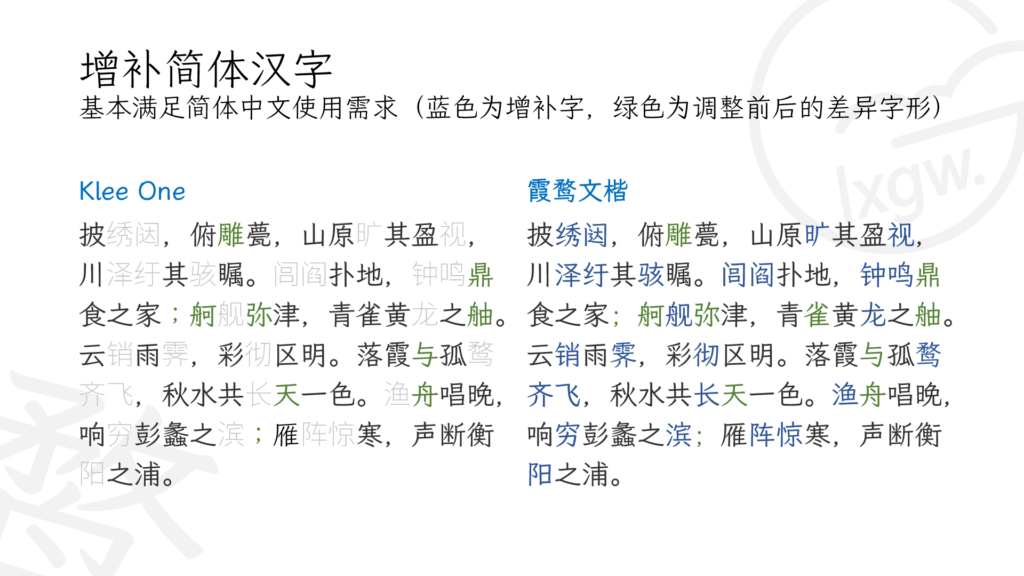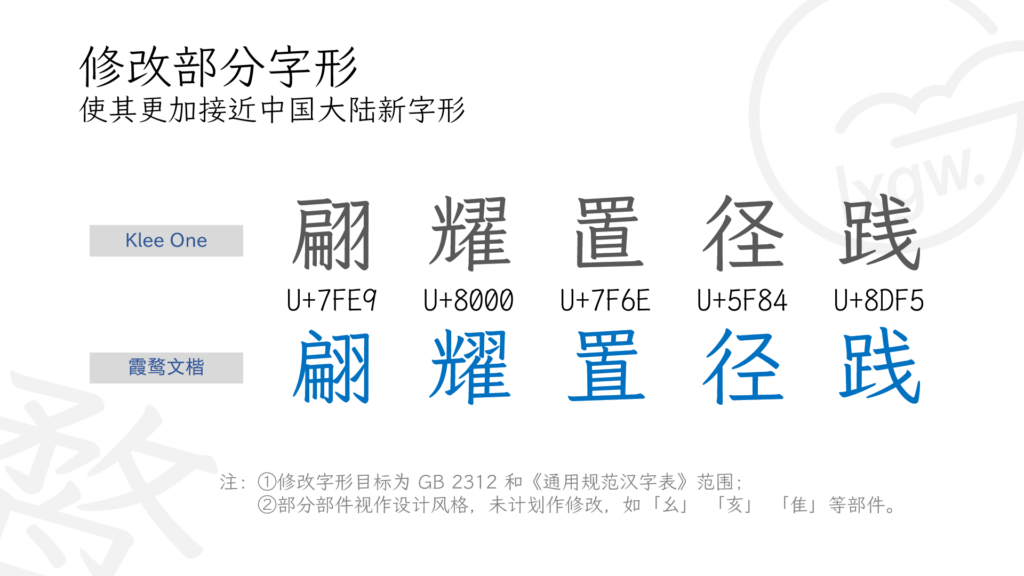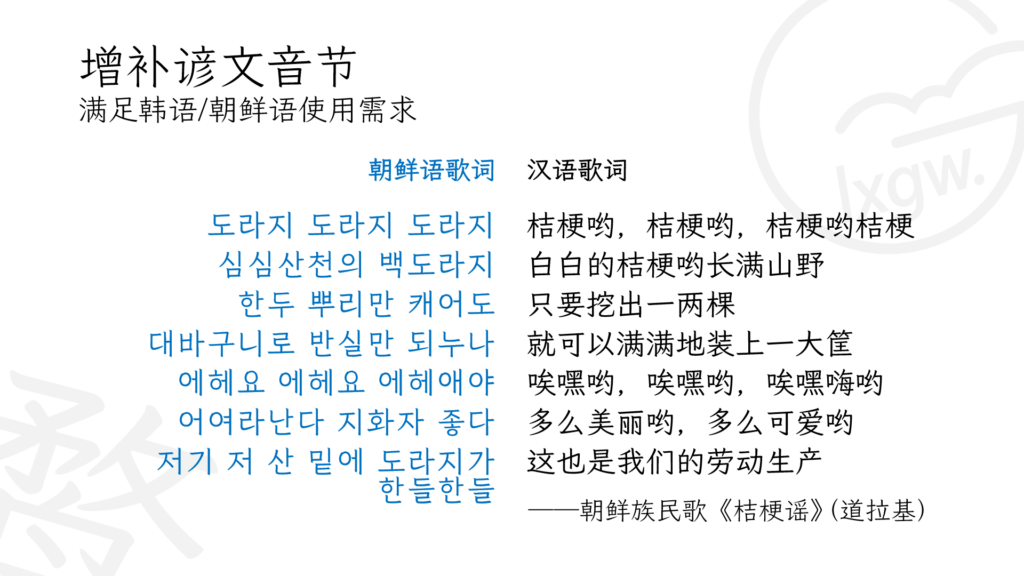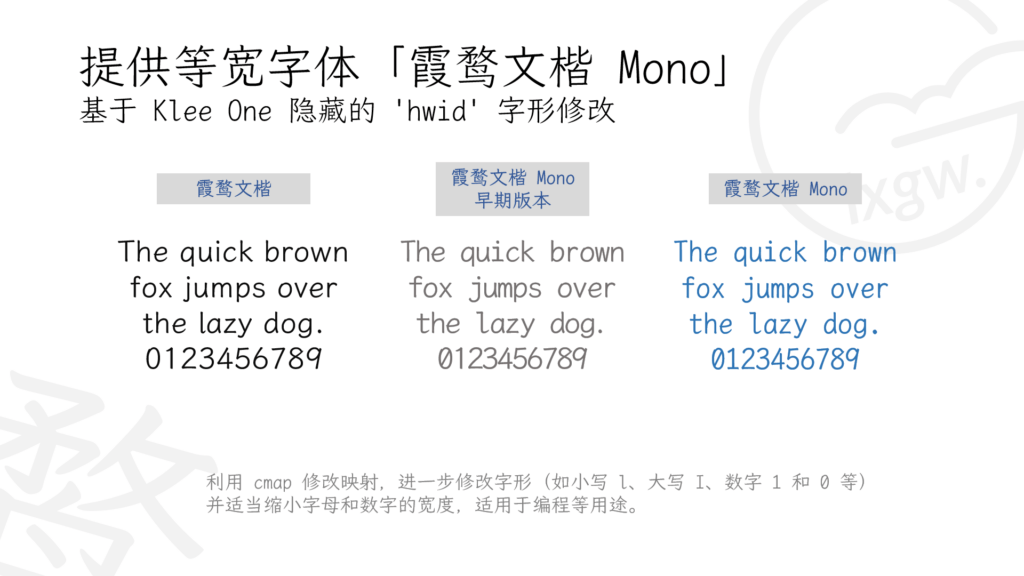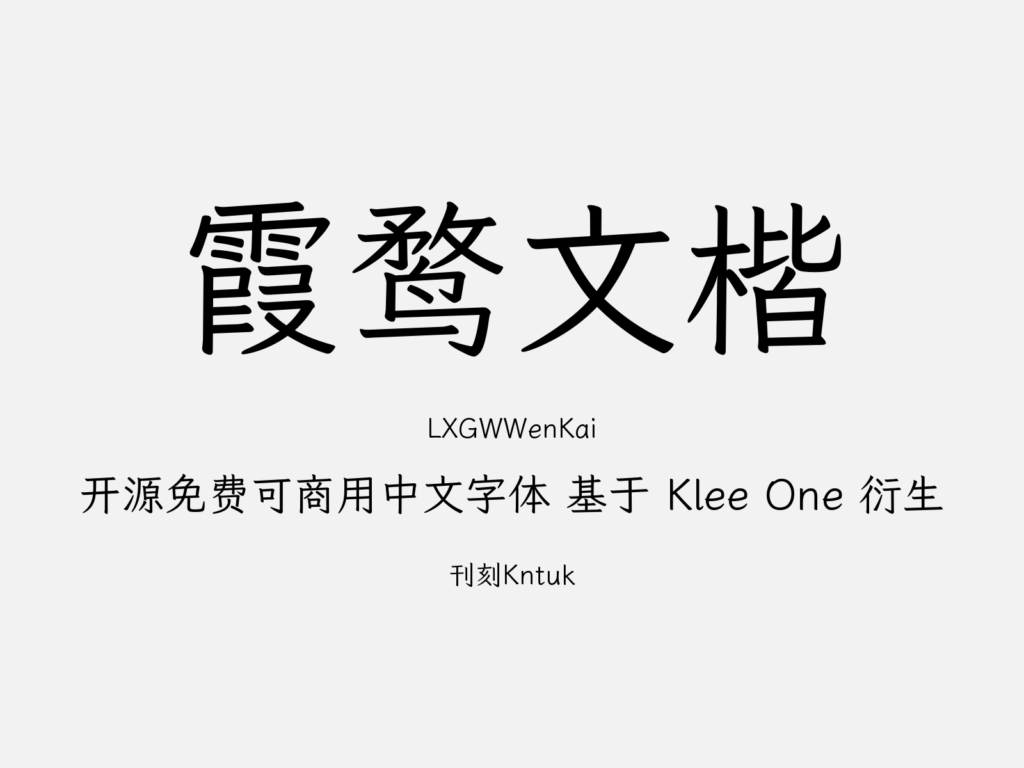
2020年12月,日本知名字体厂商FONTWORKS在GitHub上开源发布了七款日文字体,包括Train、Klee、Stick、Rock-n-Roll、Reggae、Rampart和DotGothic16,均基于SIL Open Font License 1.1授权。这七款字体各有特色,其中字符数量最多的是Klee。它带有日本教科书体风格,融合了仿宋和楷体的特点。一些字体DIY爱好者曾用仿宋等字体补全Klee,移植为iOS、Android等手机系统的美化字体,受到不少玩机发烧友欢迎。不过这种补全方式存在不足:一方面,原字体与补字体存在差异,导致不同文字混排时产生违和感,比如Klee原有汉字和后补简体字;另一方面,补字使用的字体有商业版权,补全后不可用于商业用途,还可能有侵权风险。此外,现有开源中文字体中楷体类稀少,仿宋类几乎缺失。为此,也为了丰富开源中文字体中的楷体类别,我从2021年1月20日开始尝试为高质量日文开源字体Klee One补全简繁常用字。由于该字体带有一些文艺气息,我将其命名为「霞鹜文楷」(起初觉得它适合正文阅读,所以定名“文楷”,后来发现它可能并不太适合大段正文排版,反而更适合诗词这类中等长度文本或注释排版)。Klee One的Regular字重太细不适合阅读,我选用了原字体的SemiBold字重作为Regular字重。经过长期积累,现在它已发展为支持简繁日韩的三字重字体家族。